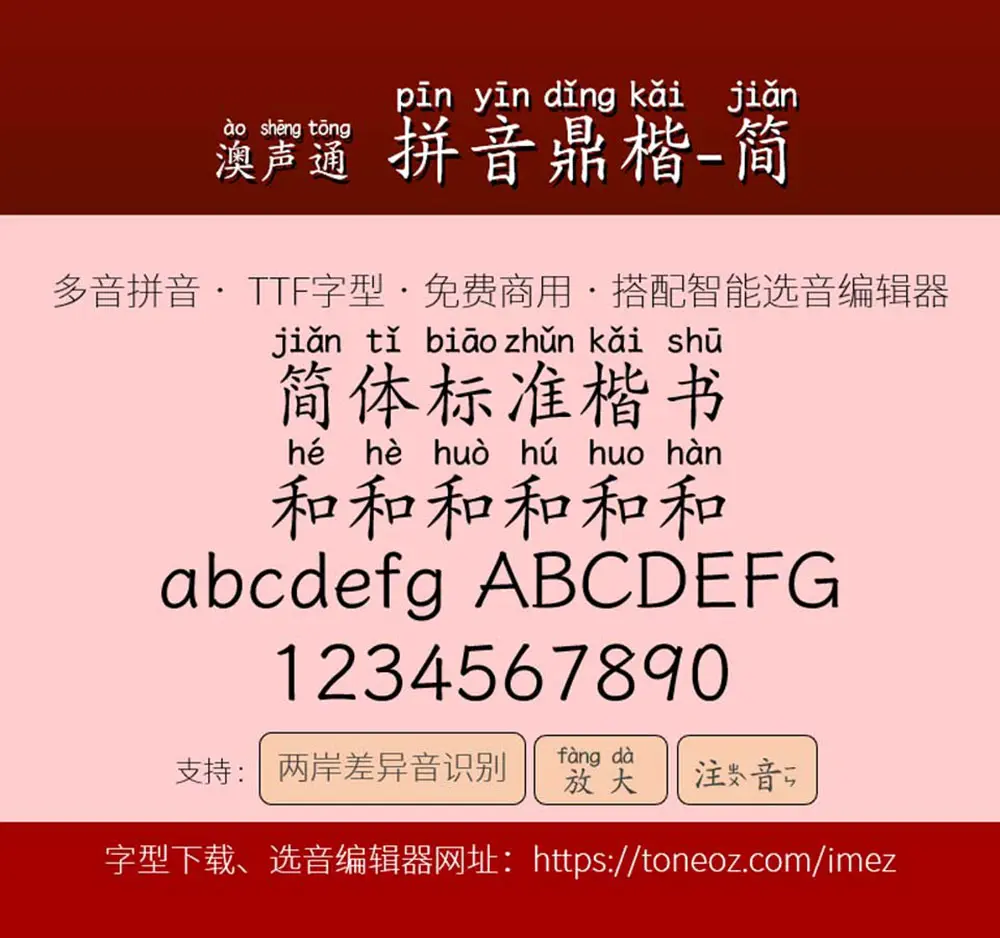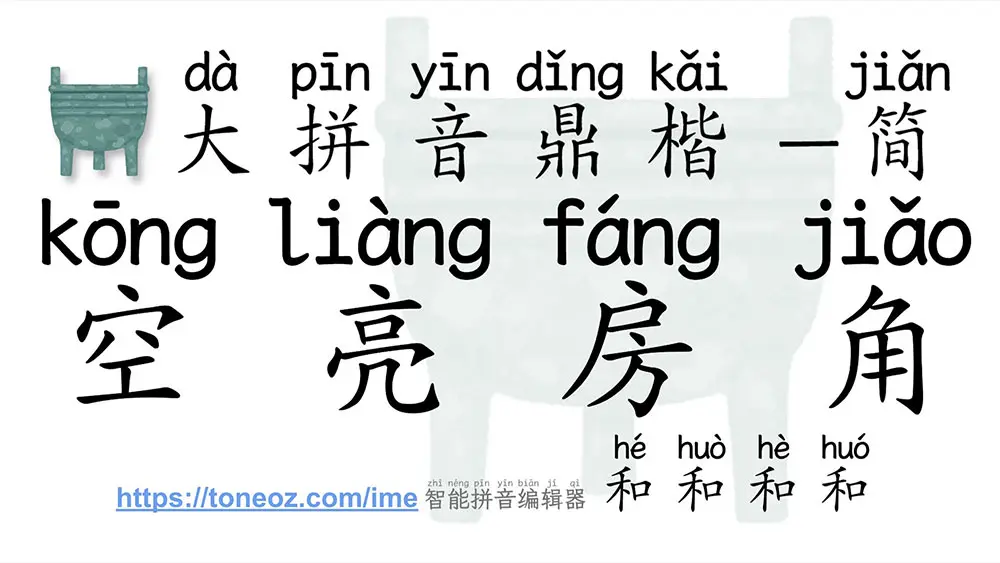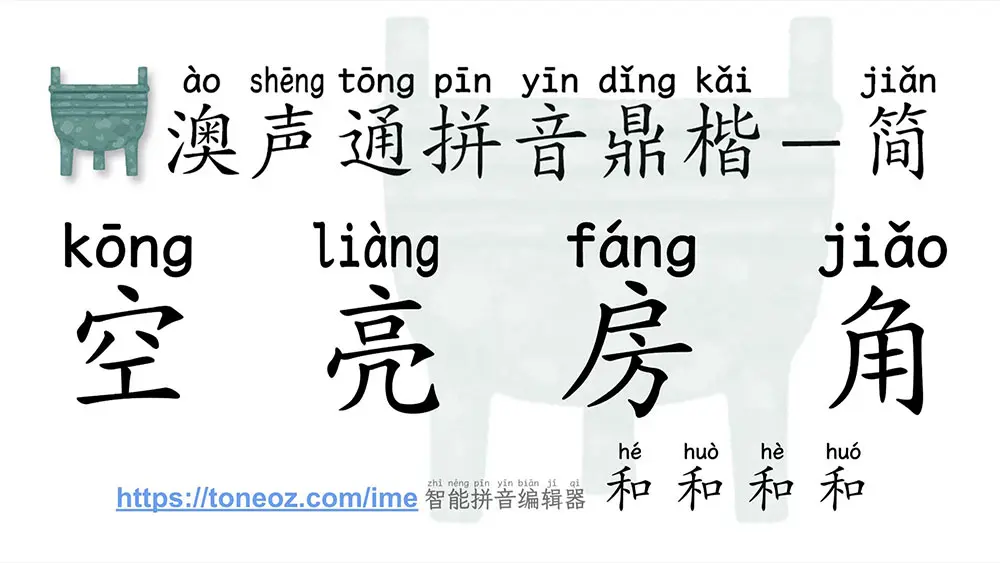
澳聲通拼音鼎楷預覽
澳聲通拼音鼎楷介紹
澳聲通拼音鼎楷是一款基於文鼎PL簡中楷的可選多音字的TrueType楷體拼音字型,滿足中文現場教學需求,搭配國際標準《ISO 7098中文羅馬字母拼寫法》的漢語拼音字型,適合熟悉羅馬字母的學習人士。
標準版(小拼音版)的大小適當不影響字距,適合文章閱讀或試卷,大拼音版本適合投影片或標題。每個字的拼音寬度不同,最短的只有一個字母,最長的字「裝zhuāng」有6個字母,大拼音字型的拼音此時可能會重疊,使用者可利用字距或者加入空白來調整。
一、澳聲通小拼音鼎楷(ToneOZ-Pinyin-Kai-Simplified)
二、澳聲通大拼音鼎楷(ToneOZ-PinyinW-Kai-Simplified)
原始楷體字型來自兩岸中文教學時常用的文鼎PL簡中楷,並根據《文鼎公眾授權書》授權許可:
拼音和非漢字字形基於FONTWORKS的 Klee One,根據 SIL Open Font License 1.1 (SIL 開源字型授權版本1.1,簡稱SIL OFL 或OFL)授權協議發佈: